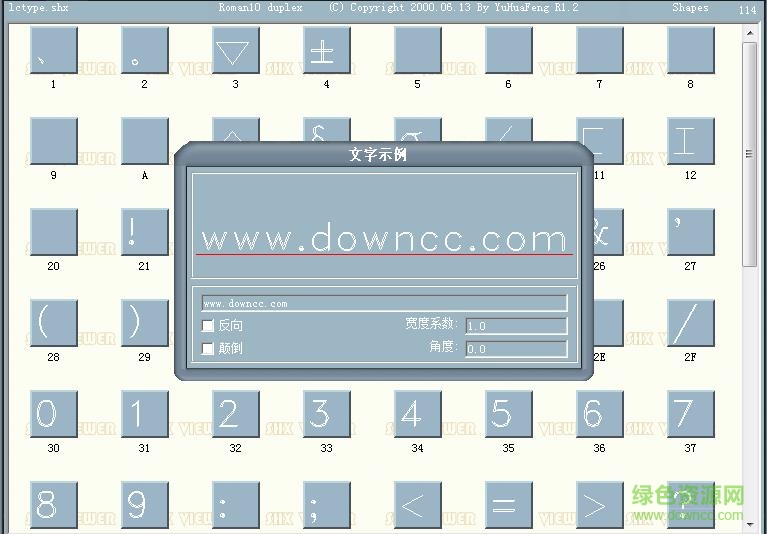
lctype.shx形文件不同于字體在于將圖形樣式進(jìn)行輸入,讓你使用專(zhuān)業(yè)的工程制圖符號(hào)以及各類(lèi)圖案,制作出不錯(cuò)的商業(yè)圖紙,快來(lái)綠色資源網(wǎng)下載吧!
lctype.shx通過(guò)在圖紙中進(jìn)行使用將讓你感受到獨(dú)特的視覺(jué)欣賞,同時(shí)也為工業(yè)制圖帶來(lái)了眾多的便利,能夠快速的調(diào)用字體文件中的符號(hào)!
1、在工業(yè)制圖,各類(lèi)圖紙制作中廣泛使用,各種行業(yè)之間的符號(hào)各不相同
2、其內(nèi)存儲(chǔ)著用戶所需的優(yōu)質(zhì)圖形符號(hào),達(dá)到了資源有效利用的效果
3、提高了用戶進(jìn)行制圖時(shí)的效率,為工程師們大大降低了制圖時(shí)間